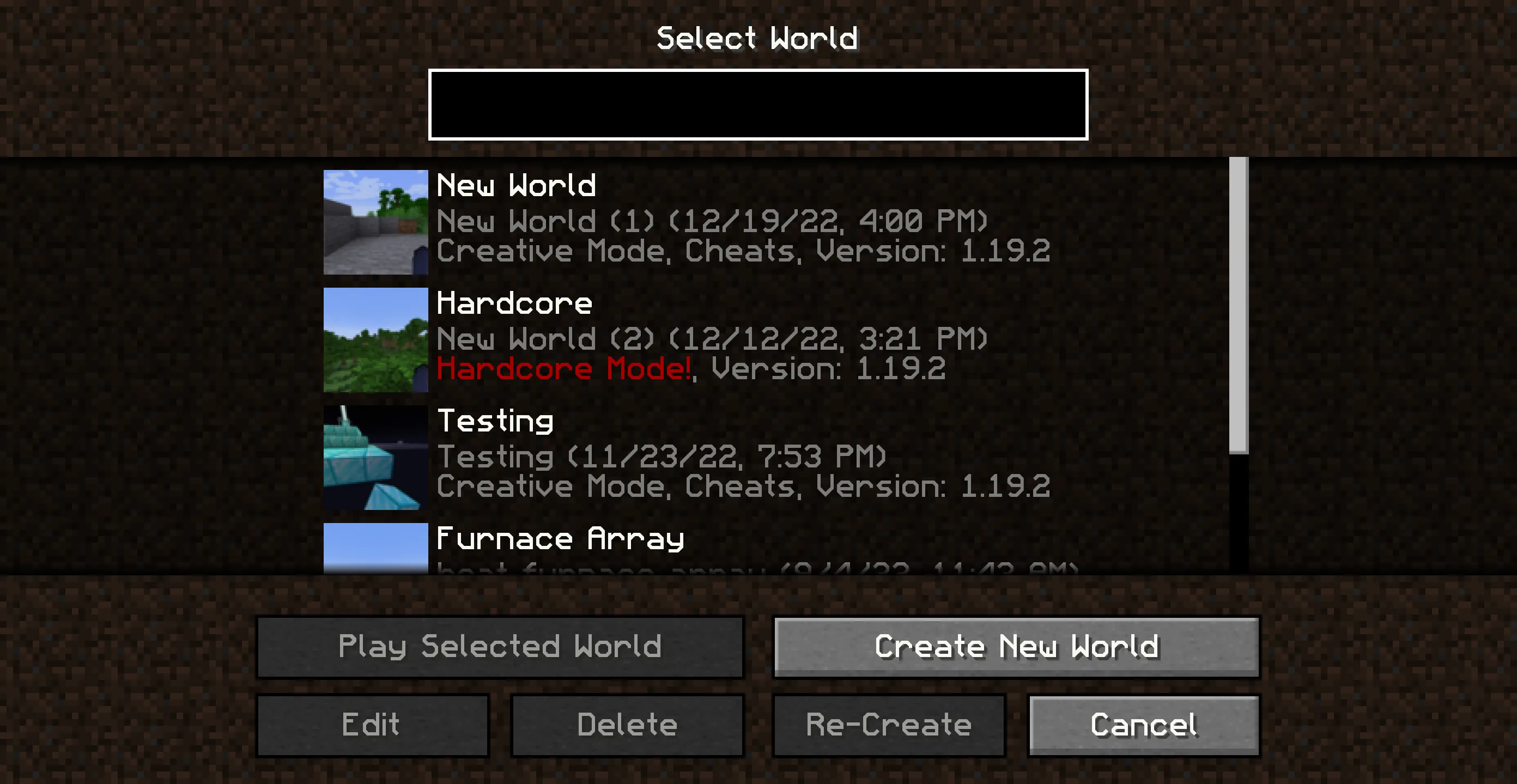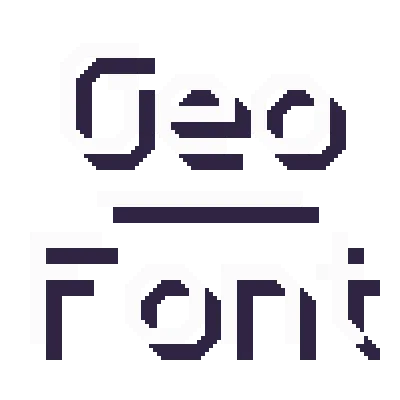
Geometric Font Legacy
Чистый и чёткий ремейк стандартного шрифта Minecraft для всех разрешений. Шрифт переработан с нуля с улучшенной консистентностью и доступен в двух вариантах.
Этот ресурспак представляет собой острый и чистый ремейк стандартного шрифта Mojangles, оптимизированный для всех разрешений. Шрифт полностью переработан с нуля как OpenType-шрифт с новыми функциями и лучшей консистентностью, предлагая более чёткий стиль, который хорошо сочетается с ванильной эстетикой.
Пакет решает проблему искажения высокоразрешающих текстур в интерфейсах, характерную для многих HD-шрифтов. Для оптимального отображения необходимо использовать версию, соответствующую вашему масштабу интерфейса (GUI scale).
Доступны два варианта шрифта: основной Geometric Font 2 и стилизованная научно-фантастическая версия Geometric Font Edge. Оба варианта обеспечивают чёткое и чистое отображение текста во всех поддерживаемых версиях Minecraft.